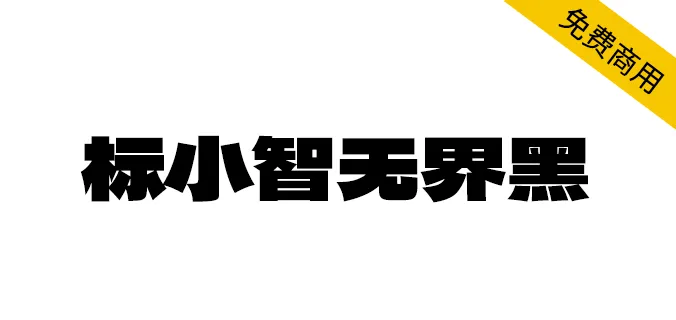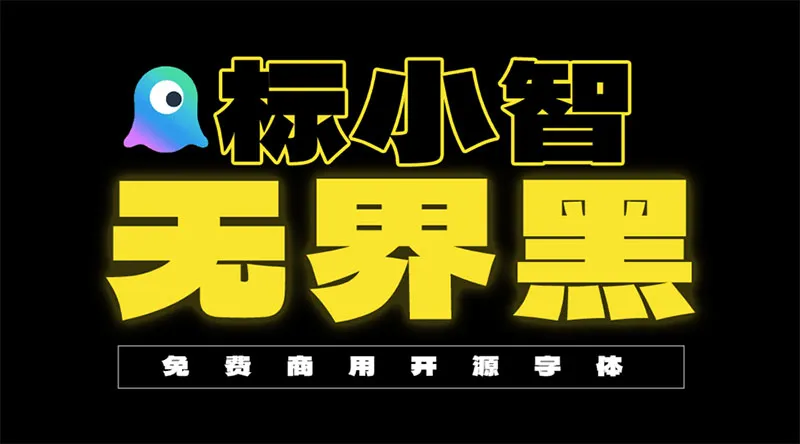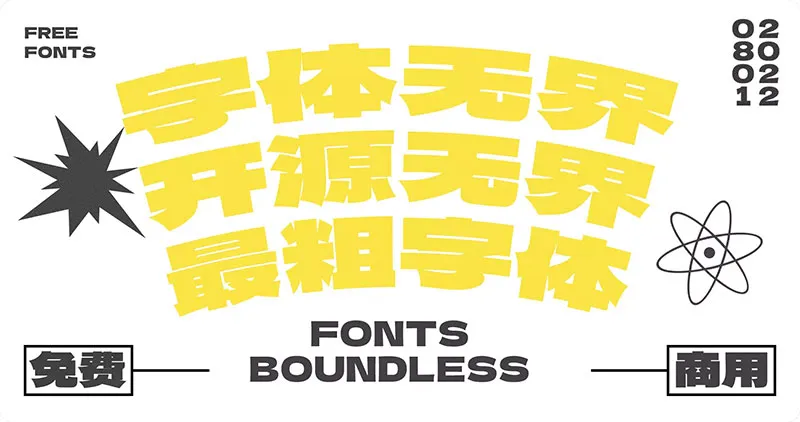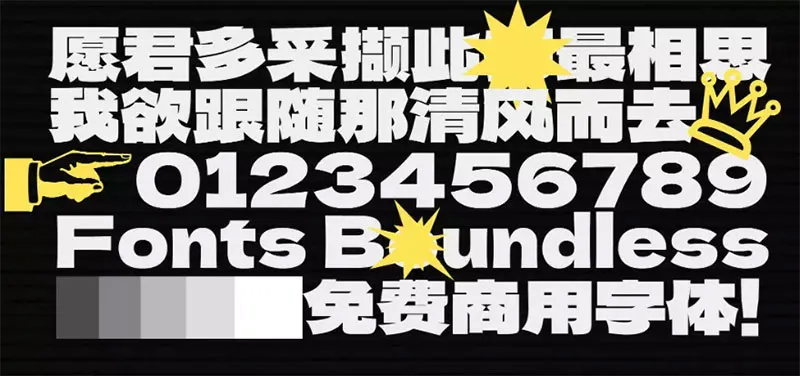
標小智無界黑是一款脫胎於日本開源字體——德拉黑體的超粗黑體,標小智無界黑按照GB2312-80字體標準來製作,從字庫角度出發,將原字體中的漢字字形更改為更加符合國標的字形,在字體細節方面做到盡善盡美。
標小智無界黑字體結構扁平,筆畫非常粗厚,同時帶有明顯的尖字體表現出非常高的穩定性和強有力的視覺表現,非常適合用於logo設計、標題、海報和包裝等場合。